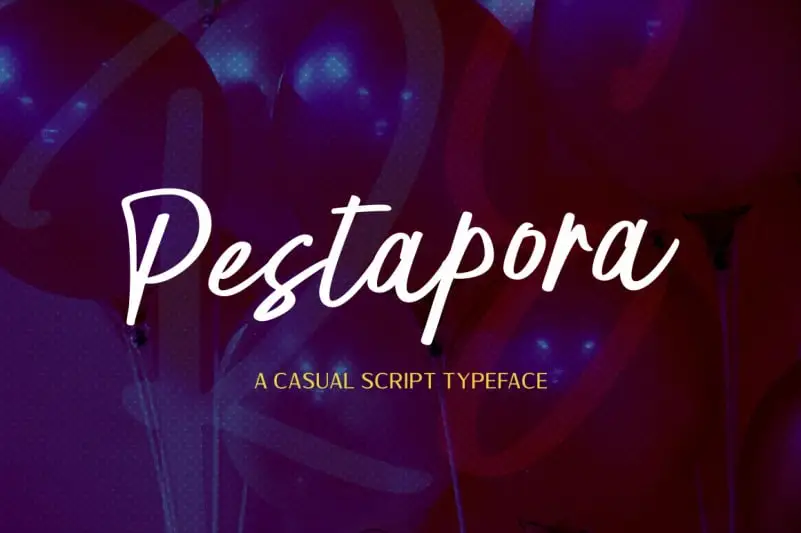
Pestapora Script Font – Fonte Grátis
Pestapora Script Font
Pestapora Script é uma fonte à mão que transmite alegria e spontaneidade com as iniciais Locomotype. Ela foi projetada para oferecer um toque autêntico, pessoal e adaptável a diversos tipos de design. Com a Pestapora, você pode aplicá-la em uma variedade de elementos, desde camisetas e convites até embalagens e aplicações de mídia social como headlines ou logotipos. Suas linhas fluidas e emotivas criam um estilo único que se destaca perfeitamente para criações digitais modernas. Ideal tanto para uma ilustração casual quanto para texturas mais elaboradas, a Pestapora Script é uma fonte versátil que atende a diversos niches de design.
Designer: Locomotype